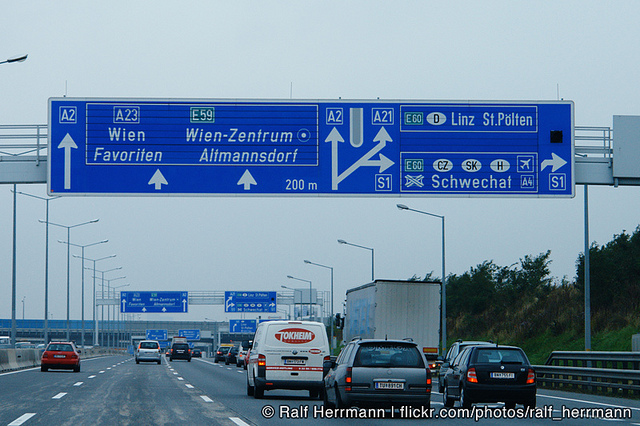
Neue Schrift für Österreichs Verkehrsschilder
Dass mit Deutschland und den Niederlanden ist natürlich Blödsinn. Das gab es offenbar Verwirrungen mit der eigentlich VMS-Schrift. Die Outline-Schrift der TERN ist ja nur ein Nebenprodukt.
Persönlich freue ich mich für Erik und das Team von IIID, aber ich habe das Österreichische System ja mehrfach untersucht und muss leider sagen: die Schrift war wirklich das geringste Übel und der Austausch hilft somit wenig.
Auch in dem Fernsehbericht sieht deutlich, dass hier nicht alles besser wird. Dieses Beispiel ist ja sehr offensichtlich:
Die alte Mittelschrift (rechts) wird nicht durch die TERN »Mittelschrift« ausgetauscht, sondern durch die neue Condensed (St. Valentin). Die Leserlichkeit verschlechtert sich. Bei der Umstellung auf die Frutiger in der Schweiz wurden die gleichen Fehler gemacht.
Auch als Typograf muss man leider sagen: der Schriftentwurf ist nicht alles. Da gäbe es, gerade bei den österreichischen Schildern, noch so viel mehr zu verbessern. Und dies hätte viel mehr Potential als nur die Schriftwahl.
Danke für den Link. Hab ichs doch geahnt, dass die Schrift nach Spiekermann’schen Inspirationen aussieht. Und offenbar sind die Oberösterreicher beim Austauschen Vorreiter, denn die iiid-Flickr-Group zeigt ausschließlich hiesige Schilder ;-)
Vielleicht will man ja durch die unübersichtlichen Schilder den Eindruck erwecken, Österreich wäre etwas größer, weil’s da so viele Orte gibt ... :neenee:
Mußten halt alle Orte auf einem Schild unterbringen.